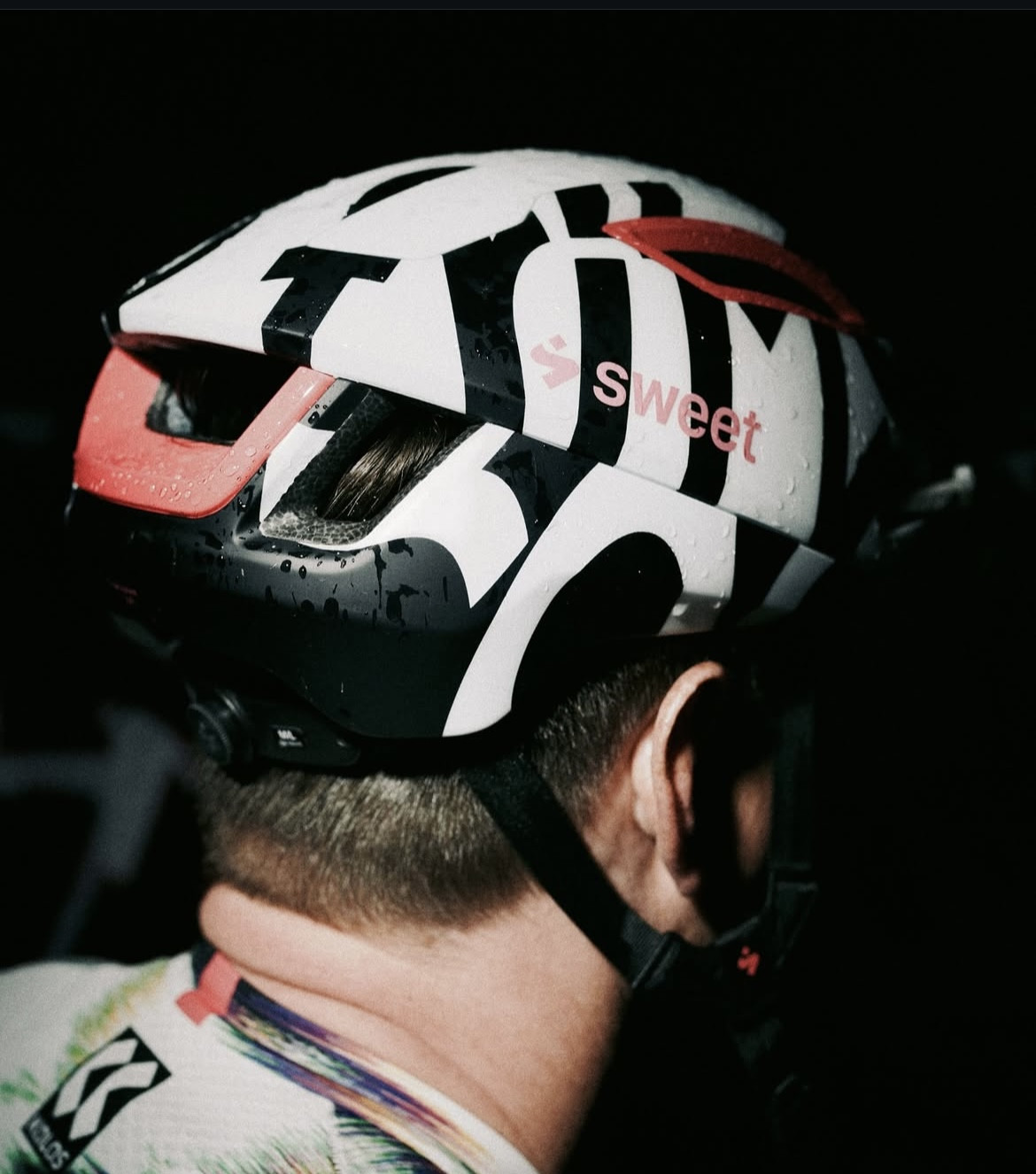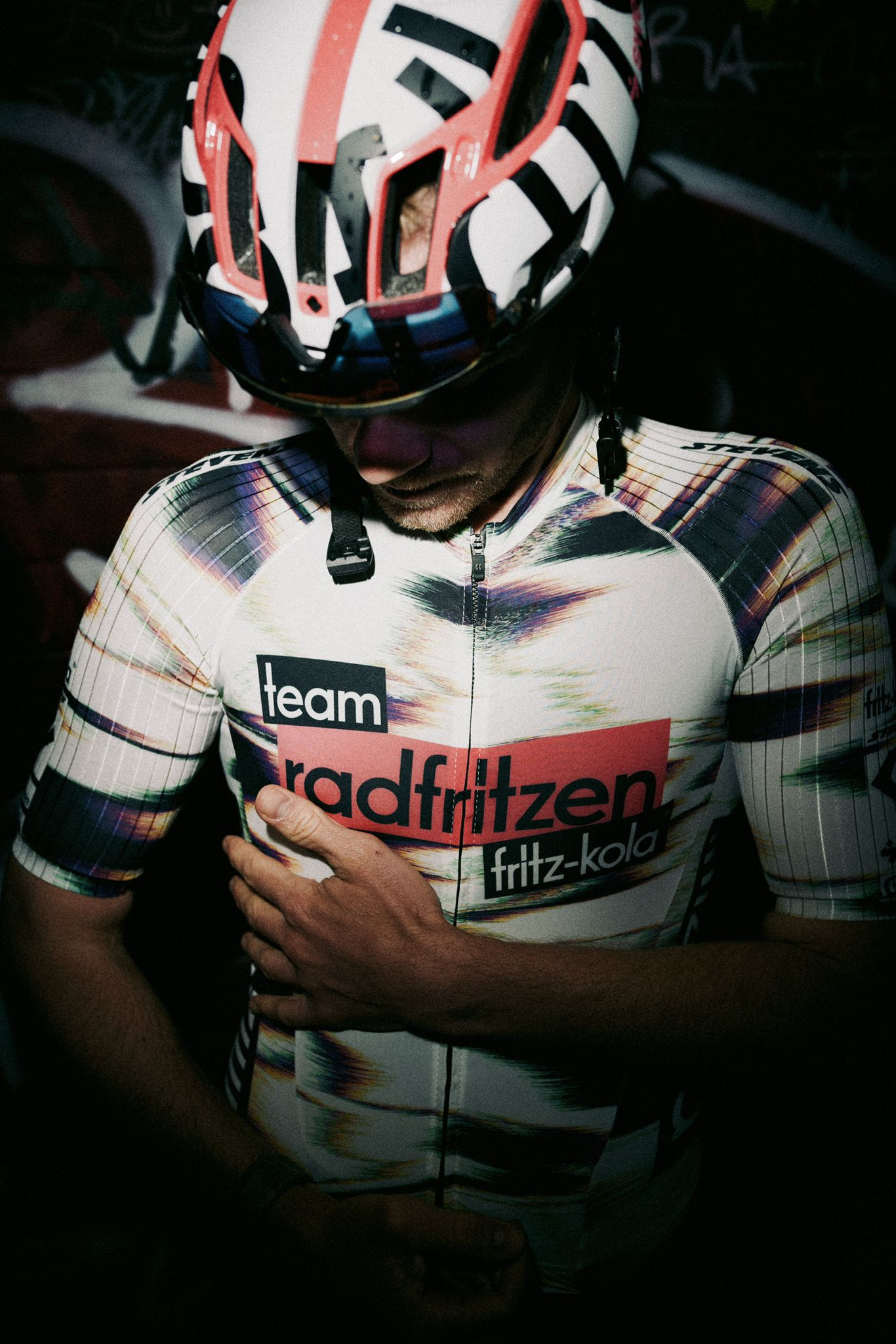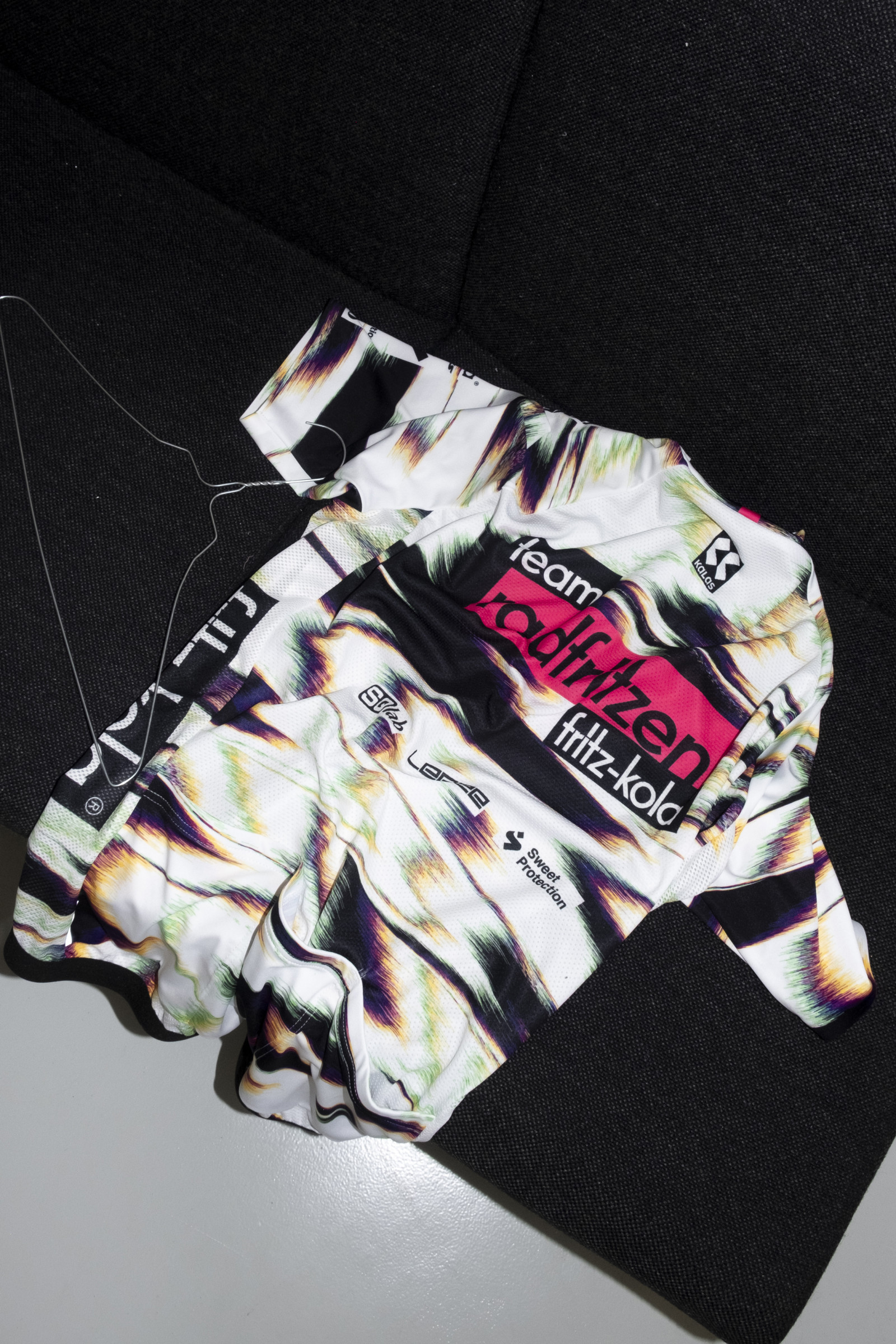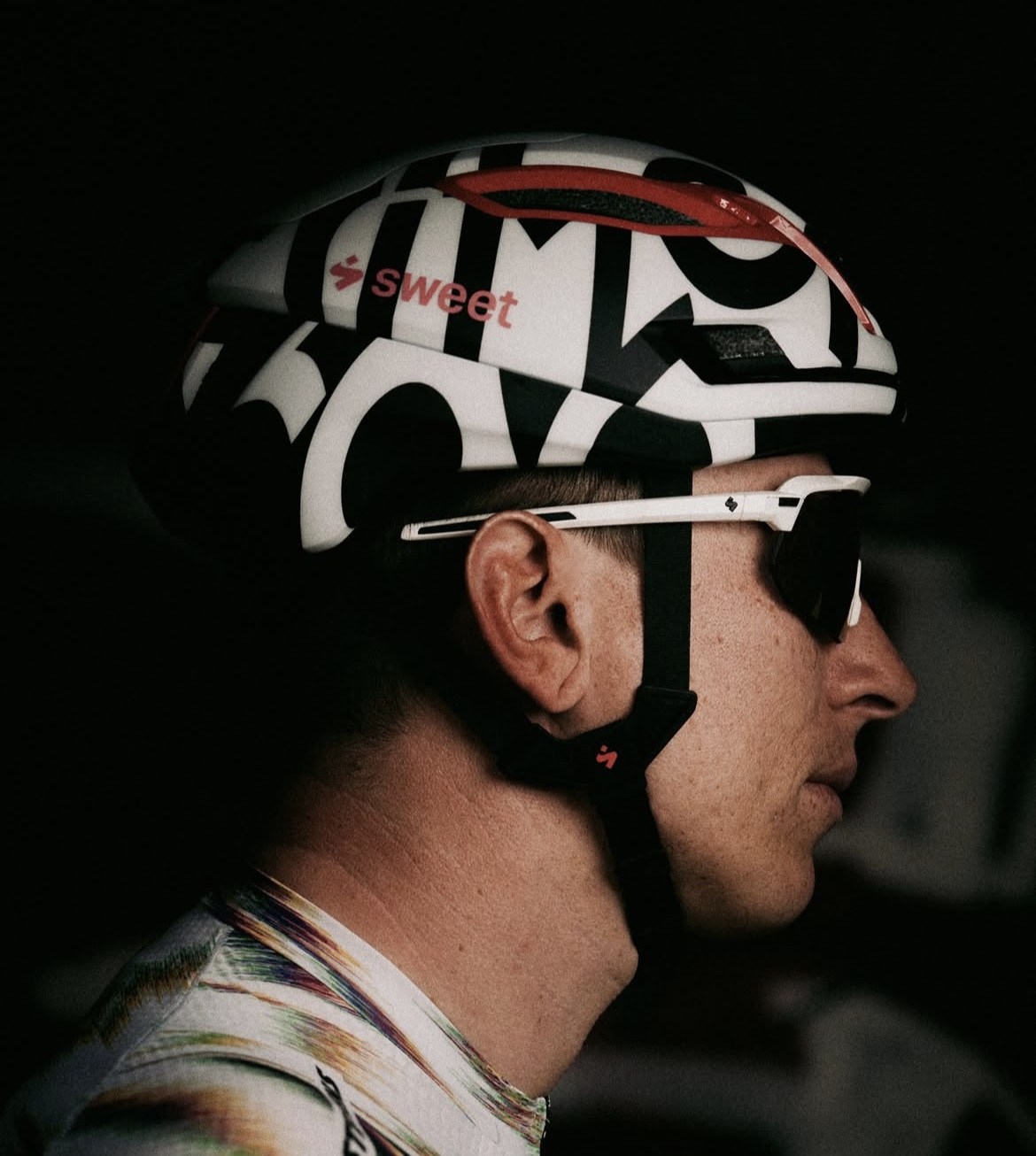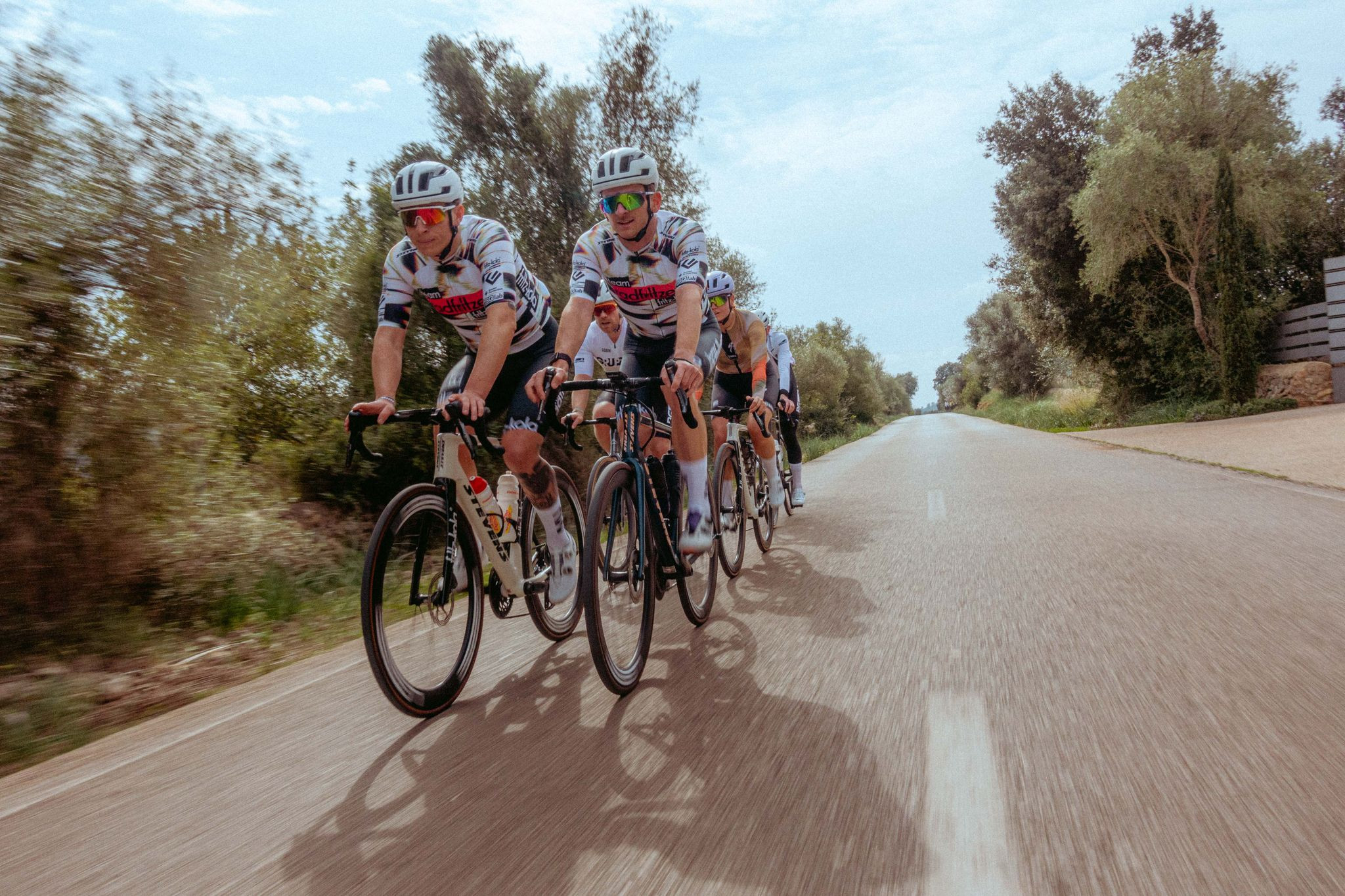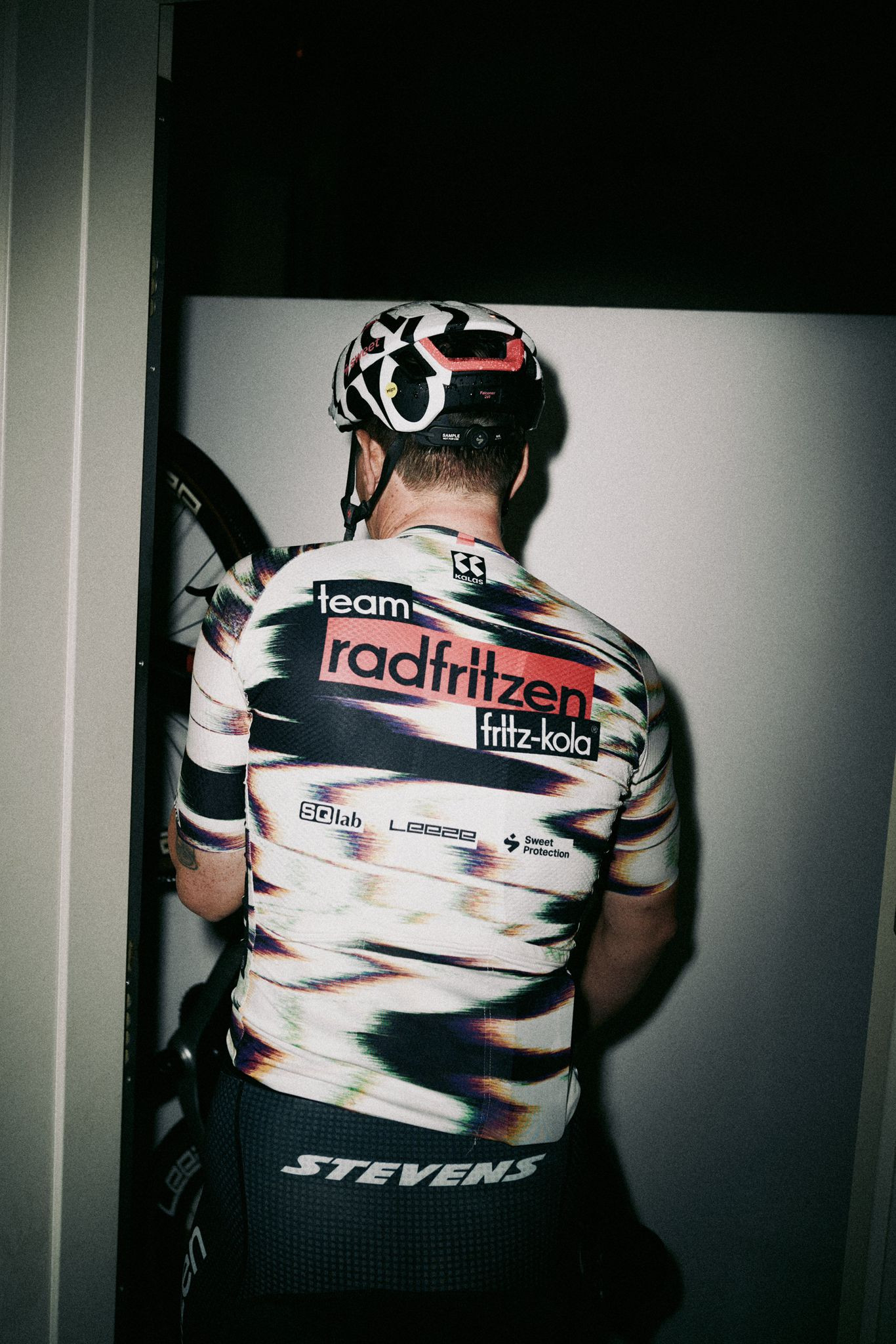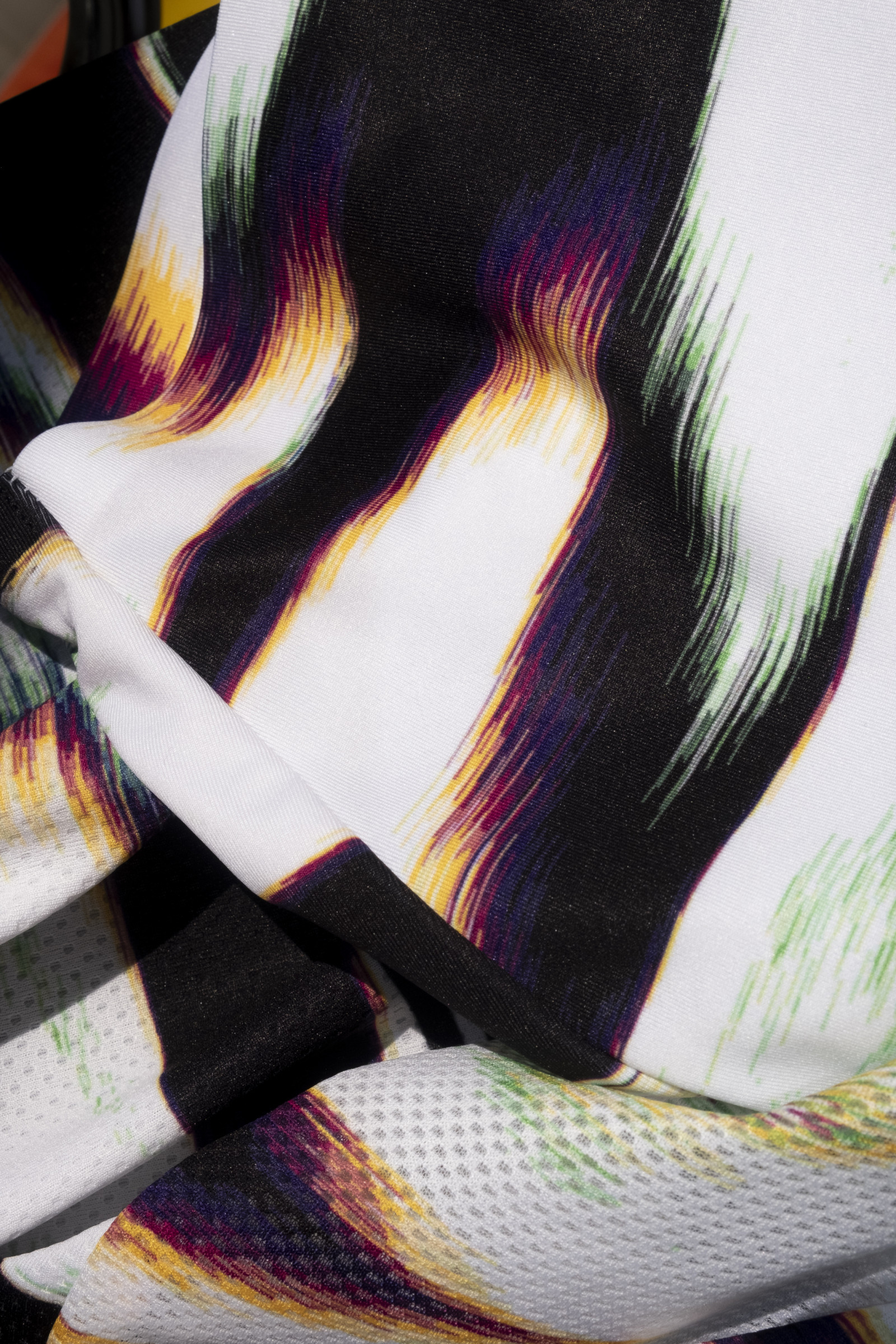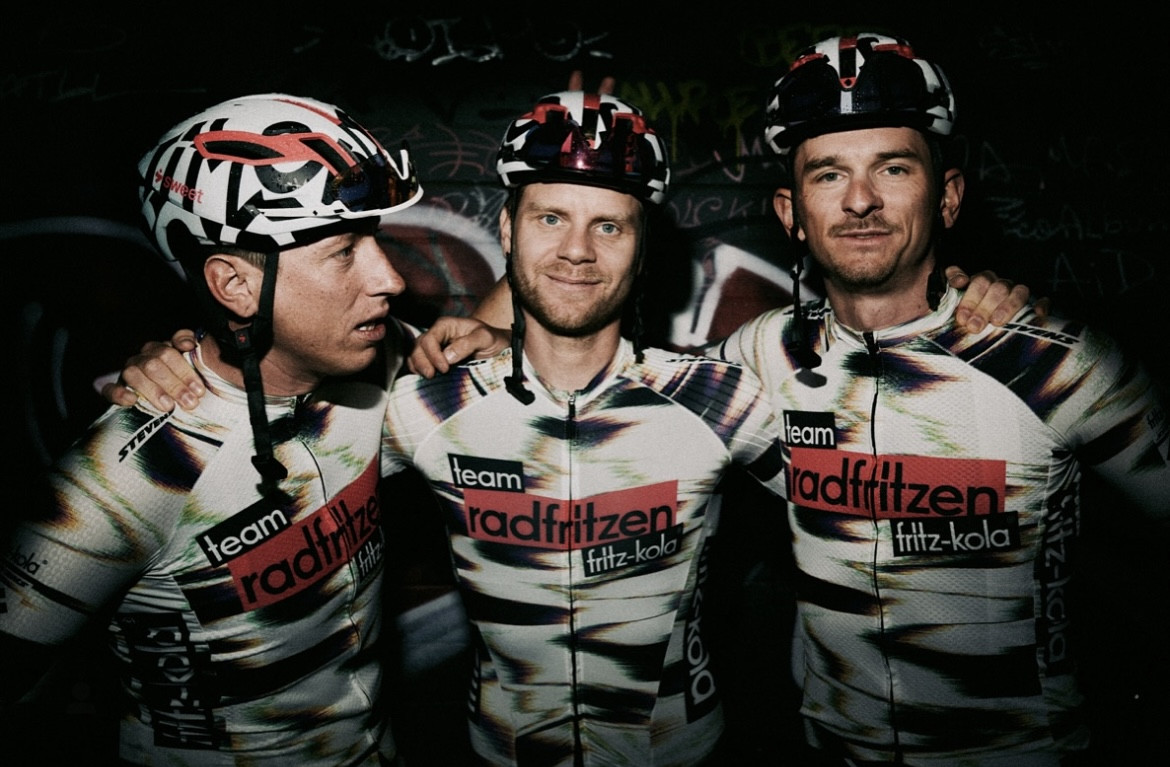
Team Radfritzen Team Kit
In Zusammenarbeit mit Team Radfritzen aus Hamburg haben wir ein neues Kit für die Saison entworfen – bestehend aus Trikot, Bib-Shorts und einem renntauglichen Einteiler.
Das Design ist von der Bewegung selbst inspiriert: Weiche, zugleich strukturierte Farbverläufe erinnern an Landschaften, die in hoher Geschwindigkeit vorbeiziehen. Ein visueller Nachhall der Fahrt, Sinnbild für Tempo, Leichtigkeit und den flüchtigen Rhythmus auf der Straße.
Ergänzend dazu entstand gemeinsam mit Sweet Protection ein individuell gestalteter Helm für das Team. Die Gestaltung ist bewusst grafisch gehalten: Großflächig verzerrte Buchstaben ziehen sich über die Helmform und werden durch den pinken Farbton akzentuiert, der auch im Teamkit aufgegriffen wird.